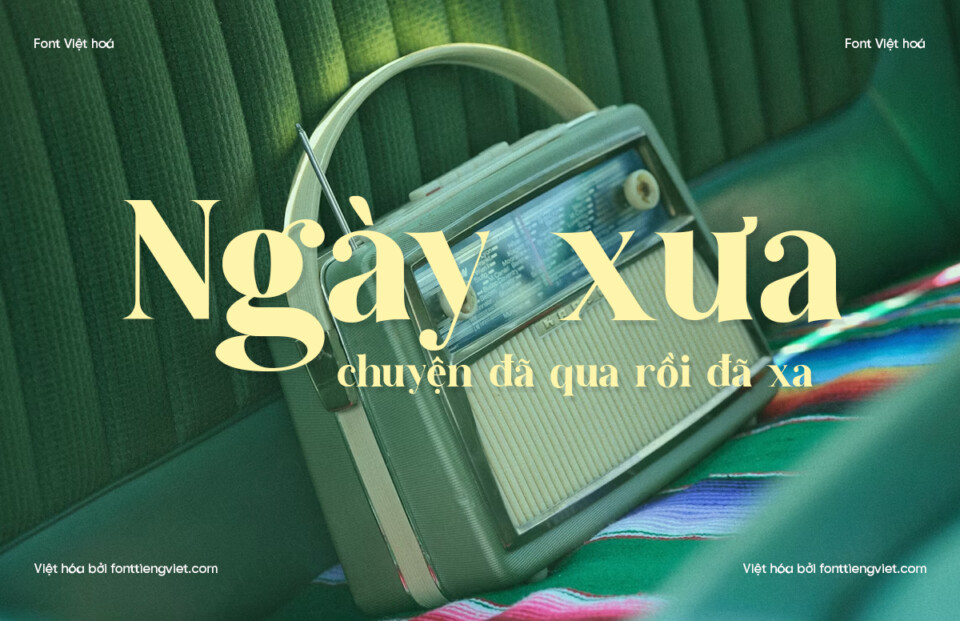
Font Việt hóa 1FTV VIP Moving
Giới thiệu về bộ Font Việt hóa 1FTV VIP Moving
Trong thế giới thiết kế đồ họa hiện đại, việc lựa chọn một bộ Font Miễn Phí chất lượng luôn là ưu tiên hàng đầu của các bạn học sinh và sinh viên. Đặc biệt, từ khóa Font Việt hóa 1FTV VIP Moving đang trở nên vô cùng thịnh hành nhờ phong cách thiết kế độc đáo và linh hoạt. Đây là một bộ font chữ mang đậm hơi thở của sự chuyển động, giúp cho các ấn phẩm truyền thông của nhà trường hoặc các bài thuyết trình nhóm trở nên sinh động và chuyên nghiệp hơn bao giờ hết. Với việc được Việt hóa chỉn chu, người dùng sẽ không còn lo lắng về lỗi hiển thị dấu tiếng Việt, giúp quy trình sáng tạo trở nên mượt mà và hiệu quả.
Đặc điểm nổi bật của Font Việt hóa 1FTV VIP Moving
Phong cách thiết kế hiện đại và năng động
Đúng như tên gọi “Moving”, bộ font này sở hữu những đường nét thanh thoát nhưng không kém phần mạnh mẽ, tạo cảm giác về sự bứt phá và tiến lên phía trước. Font Việt hóa 1FTV VIP Moving rất phù hợp để làm tiêu đề cho các báo cáo ngoại khóa, làm poster sự kiện thể thao hoặc thiết kế áo lớp. Sự kết hợp giữa các nét dày và mỏng được tính toán kỹ lưỡng giúp font chữ có độ tương phản tốt, dễ đọc ngay cả khi quan sát từ xa. Đây chính là lựa chọn hoàn hảo cho những ai muốn tìm kiếm sự mới mẻ thay vì những kiểu chữ truyền thống nhàm chán.
Khả năng ứng dụng đa dạng trong học tập
Đối với các bạn học sinh, bộ font này có thể dùng để trang trí bài tập làm văn trên máy tính hoặc tạo ra những tấm thiệp chúc mừng thầy cô đầy ý nghĩa. Trong môi trường giáo dục, thầy cô cũng có thể sử dụng font chữ này để làm slide giảng dạy thêm phần lôi cuốn, giúp học sinh dễ dàng nắm bắt kiến thức thông qua những dòng chữ rõ ràng và thẩm mỹ.
Lưu ý khi phối hợp cùng các bộ font khác
Để đạt được hiệu quả thị giác cao nhất, người dùng nên kết hợp bộ font chữ đặc biệt này với các kiểu chữ không chân (sans-serif) cơ bản. Điều này sẽ giúp tiêu đề được làm nổi bật hoàn toàn, tạo nên một bố cục hài hòa và chuyên nghiệp cho tổng thể trang giấy hoặc bản trình chiếu. Sự đơn giản nhưng tinh tế chính là chìa khóa để thu hút người xem.
Kết luận về Font Việt hóa 1FTV VIP Moving
Tổng kết lại, việc sở hữu một bộ font chữ đẹp và chuẩn tiếng Việt là điều vô cùng cần thiết trong thời đại số hóa hiện nay. Font Việt hóa 1FTV VIP Moving không chỉ mang lại giá trị thẩm mỹ cao mà còn là công cụ hỗ trợ đắc lực cho các hoạt động học tập và sáng tạo tại nhà trường. Hãy tận dụng ngay cơ hội này để tải Font Miễn Phí, Font Việt Hóa, Font Việt hóa 1FTV VIP Moving về máy và làm mới những dự án của riêng mình. Hy vọng bài viết này đã mang đến cho bạn những thông tin hữu ích và nguồn cảm hứng bất tận để biến những ý tưởng trên giấy thành những sản phẩm thiết kế ấn tượng nhất trong tương lai gần.